(下)Behance大神总结的 2019 设计流行趋势
三、排版趋势
3.1 越大,越大胆越好
我们发现在每年的预测中,大胆的排版成为了一种趋势。使用极简主义大字是个不错的选择,否则设计看起来会很拥挤且没有吸引力。
3.2 字体设计
很多大品牌都有自己的字体,保证品牌的独特性。
四、品牌、logo 设计趋势
4.1使用颜色通道
2018 年我们就看见了这一趋势,但在 2019 年仍然是新鲜的概念,使用颜色通道可以创建显著的视觉效果。
4.2 品牌插画
在所有的领域我们都能看到插画,并且得到人们深深的喜爱。好的插画绝对可以让单一的海报,品牌和印刷物料脱颖而出。
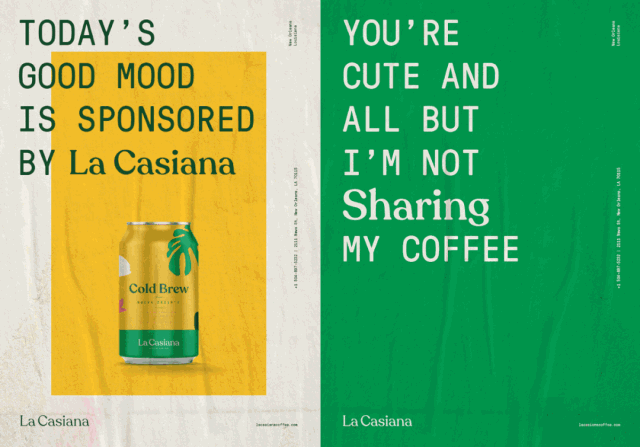
4.3 动态Logo
所有的设计领域都有动效的应用,在logo中也不例外。
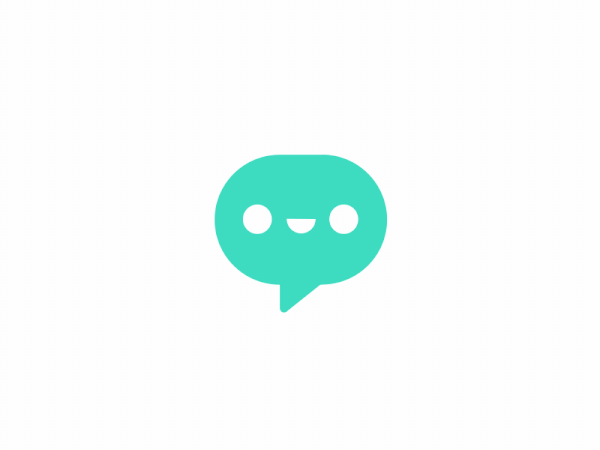
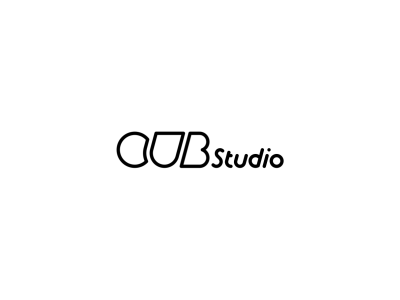
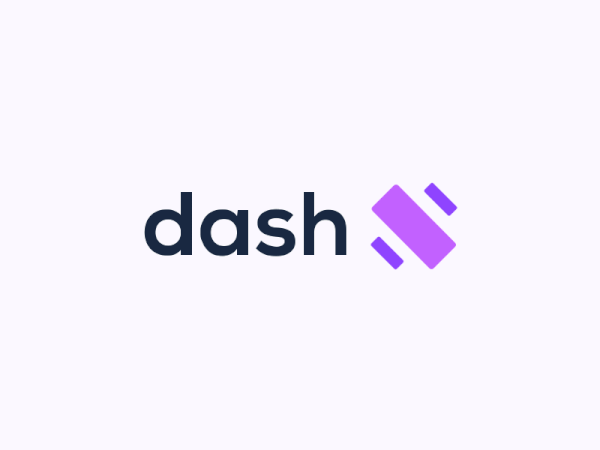
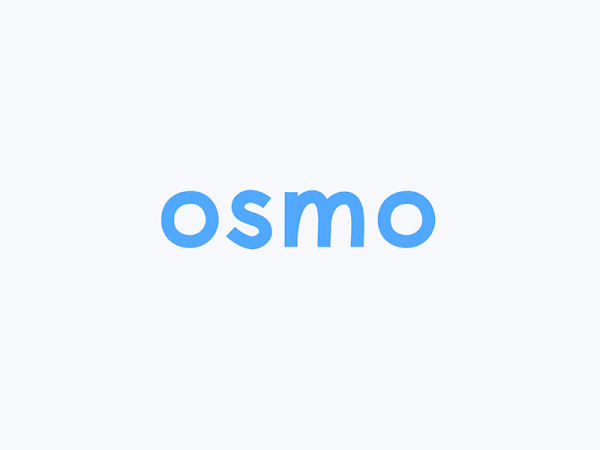
五、动态图形趋势
5.1 杂色
2D 动画中经常会看到杂色的效果,在3d动画中也有所应用。
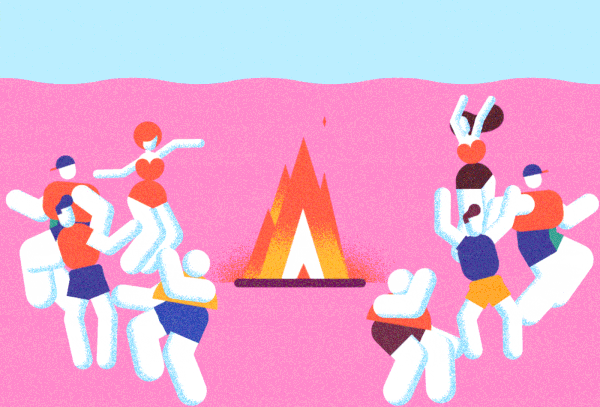
5.2 扁平2D动效
2D设计中使用的阴影和渐变来表现轻写实的趋势被替代,但在动效中扁平风格仍然风靡。二维艺术空间运动大多有故事情节、场景,主要动作通过漫画的形式展现。流畅的过渡可以吸引用户注意力,要表达的内容更容易理解。
5.3 3D动效
3D 动效视觉表现力强,无论什么产品使用 3D 动效,都会增加产品的表现力。绝大部分的大品牌在广告宣传中使用 3D 动效,因为它有很高的转化率。
六、包装设计趋势
6.1大胆用色
大胆用色的包装是 2019 年设计趋势之首。
6.2 非传统材质
采用独特材质的包装设计,是设计领域的重要方向。使用零浪费、可降解生物材料,可食用、纤维素材料,是创新品牌提倡的理念。
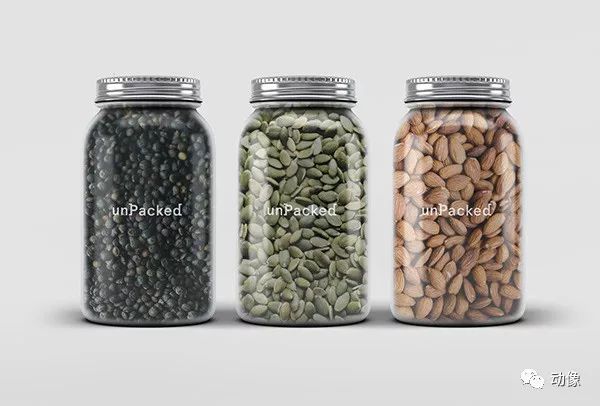
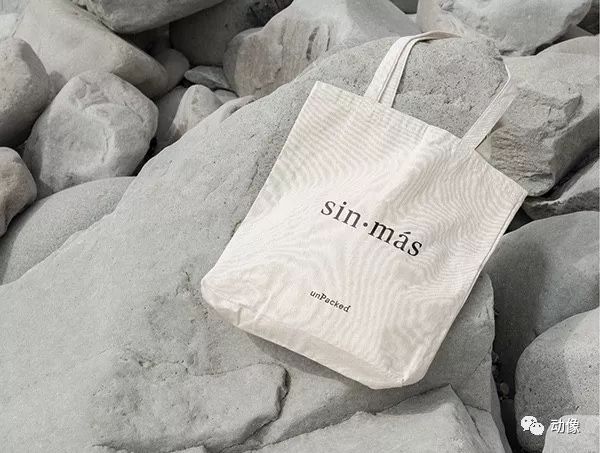
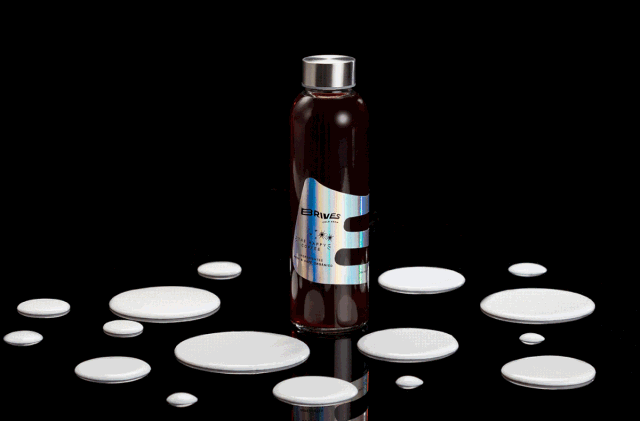
6.3 天然材料
天然材料,如木头永远是包装设计的趋势。可回收的材料如皮革、木材、厚纸板、纤维素等,都是包装设计的天然材料。
6.4 大字
如上所述,大字体设计是 2019 年必然趋势。一个大胆的包装,一个大词就够了。大小字母的组合,就可以做出一个漂亮的包装。
6.5 极简主义
少即是多!如果包装使用大量的文本和不同的字体,会是一个凌乱的设计。
6.6 插图
2019 年插图占据所有的设计领域,包装设计也不例外。